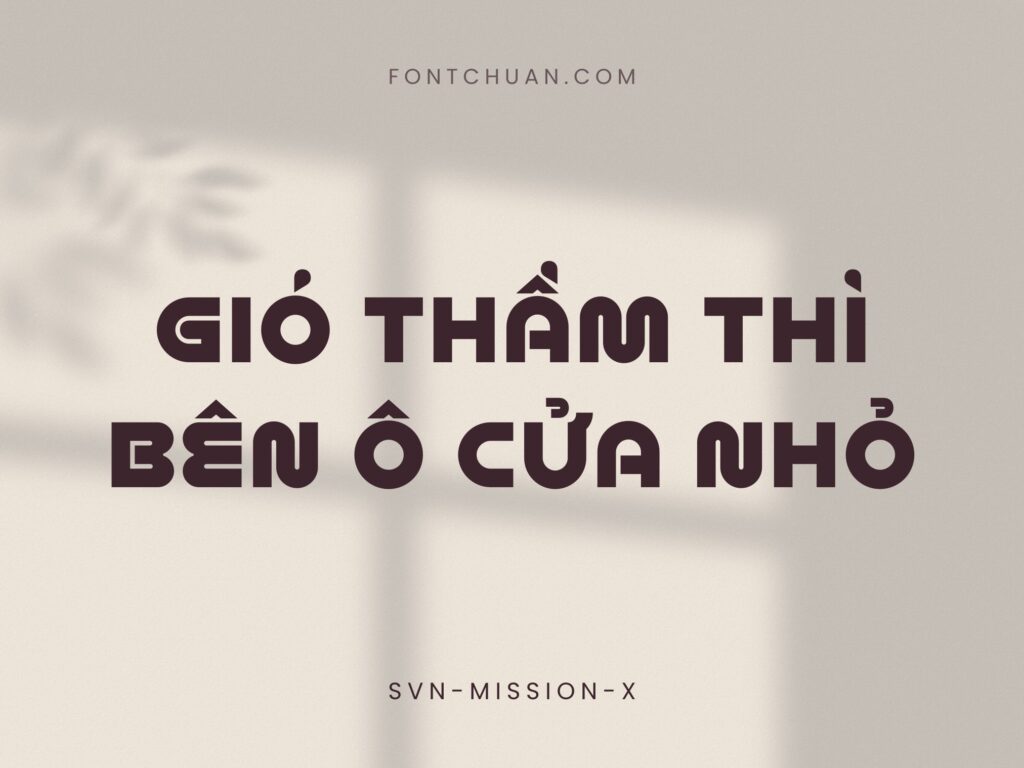
Font SVN Mission X Việt Hóa
Font SVN Mission X là phiên bản Việt hóa của kiểu chữ Mission X, được thực hiện bởi STYLEno.1 Fonts. Mission X là một kiểu chữ sans-serif siêu hiện đại, lấy cảm hứng từ thẩm mỹ của Stanley Kubrick, các bộ phim khoa học viễn tưởng và chủ đề không gian. Font này phù hợp cho các thương hiệu hoặc thiết kế hướng tới phong cách công nghệ cao, hiện đại và tương lai. Mission X bao gồm đầy đủ các ký tự chữ hoa, chữ thường, chữ số và dấu câu, hỗ trợ đa ngôn ngữ. Font này lý tưởng cho nhiều mục đích sử dụng khác nhau như thiết kế logo, tiêu đề, bao bì sản phẩm và các ấn phẩm truyền thông.
SVN Mission X lý tưởng cho các dự án thiết kế yêu cầu sự hiện đại và phong cách tương lai, như thiết kế logo, tiêu đề, bao bì sản phẩm và các ấn phẩm truyền thông. Các ngành nghề như công nghệ, quảng cáo và giáo dục có thể tận dụng font này để tạo điểm nhấn trong thiết kế. Ngoài ra, font cũng thích hợp cho các sự kiện như Tết, Giáng sinh, Valentine và các lễ hội khác.